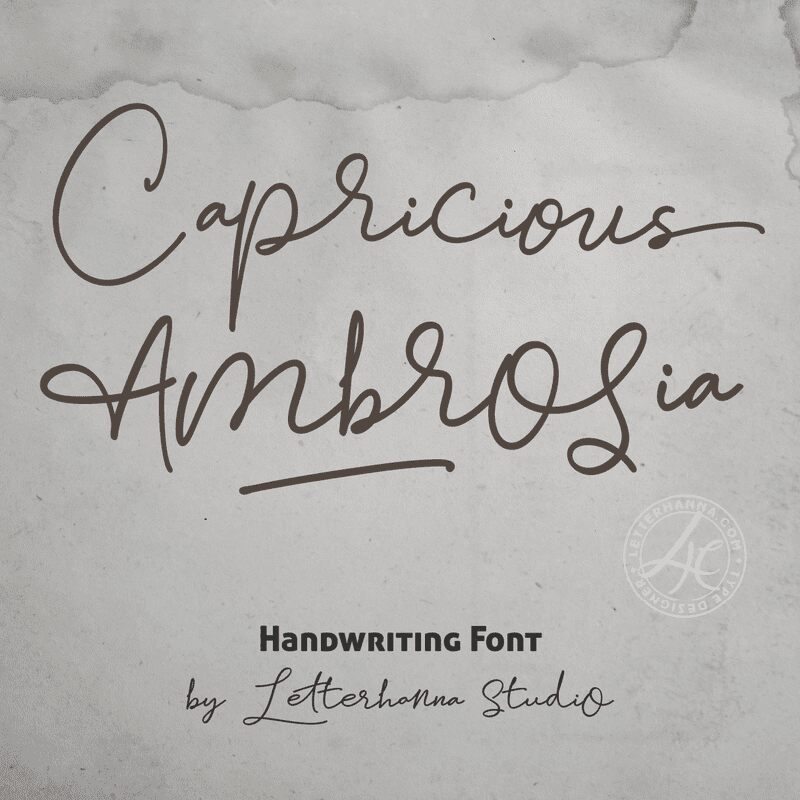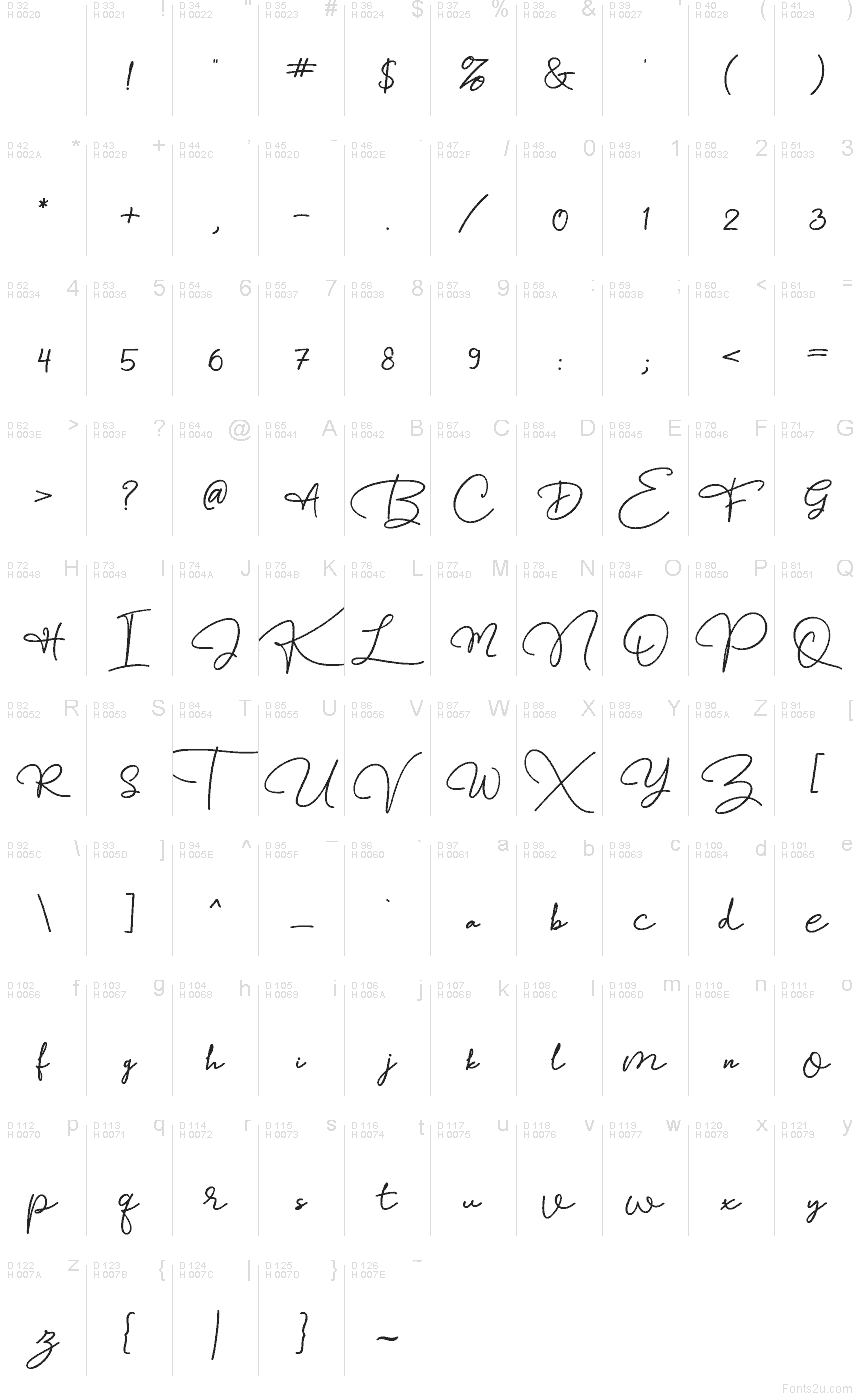
Capricious Ambrosia di Rinaldo Hasibuan di Letterhanna Studio è un carattere calligrafico che evoca la sensazione dell'inchiostro fresco che scorre su carta liscia. I suoi tratti sottili e leggeri, uniti a legature allungate, donano a ogni parola un ritmo vivace: elegante, ma con un tocco squisitamente umano. Il movimento naturale delle lettere trasmette l'autenticità di un messaggio scritto a mano, lontano dalla freddezza di uno script aziendale.
Utilizza Capricious Ambrosia per donare un tocco di grazia a partecipazioni di nozze, branding di boutique, packaging di prodotti di bellezza, citazioni su Instagram, biglietti d'auguri, lookbook e menu di caffetterie. Questo font gratuito mantiene una leggibilità ottimale quando ha spazio per respirare e viene utilizzato con una dimensione leggermente maggiore nei testi lunghi. Abbinalo a un sans-serif geometrico pulito per il testo principale, così da mantenere intatto il fascino e garantire una lettura senza sforzo.
Introducing "Capricious Ambrosia"  a captivating handwritten font that embodies the essence of unpredictability and delight. Each stroke of this font is a wild card, carrying a sense of unexpected charm. Just like a nomad's journey filled with surprises, "Capricious Ambrosia" adds an element of mystique to your designs. Whether you're seeking a font that breaks conventions or a touch of divine creativity, let "Capricious Ambrosia" guide your artistic path. Embrace the beauty of unpredictability and savor the unique flavor it brings to your projects.